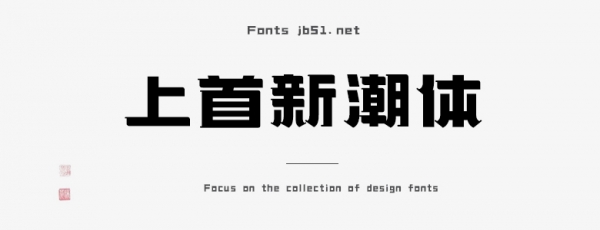
上首新潮體是由上首造字字庫出品的字體,字體不拘一格,整體滿足現(xiàn)代審美,科技、創(chuàng)意、藝術(shù)的結(jié)合,適用于搭配標(biāo)志、廣告標(biāo)語、商業(yè)廣告等高端屬性,需要的朋友可以前來本站下載。
上首新潮體,簡體中文約6763字,字體不拘一格,代表著新的趨勢,其字體整體滿足現(xiàn)代審美,科技、創(chuàng)意、藝術(shù)的結(jié)合。適用于搭配標(biāo)志、廣告標(biāo)語、商業(yè)廣告等高端屬性。